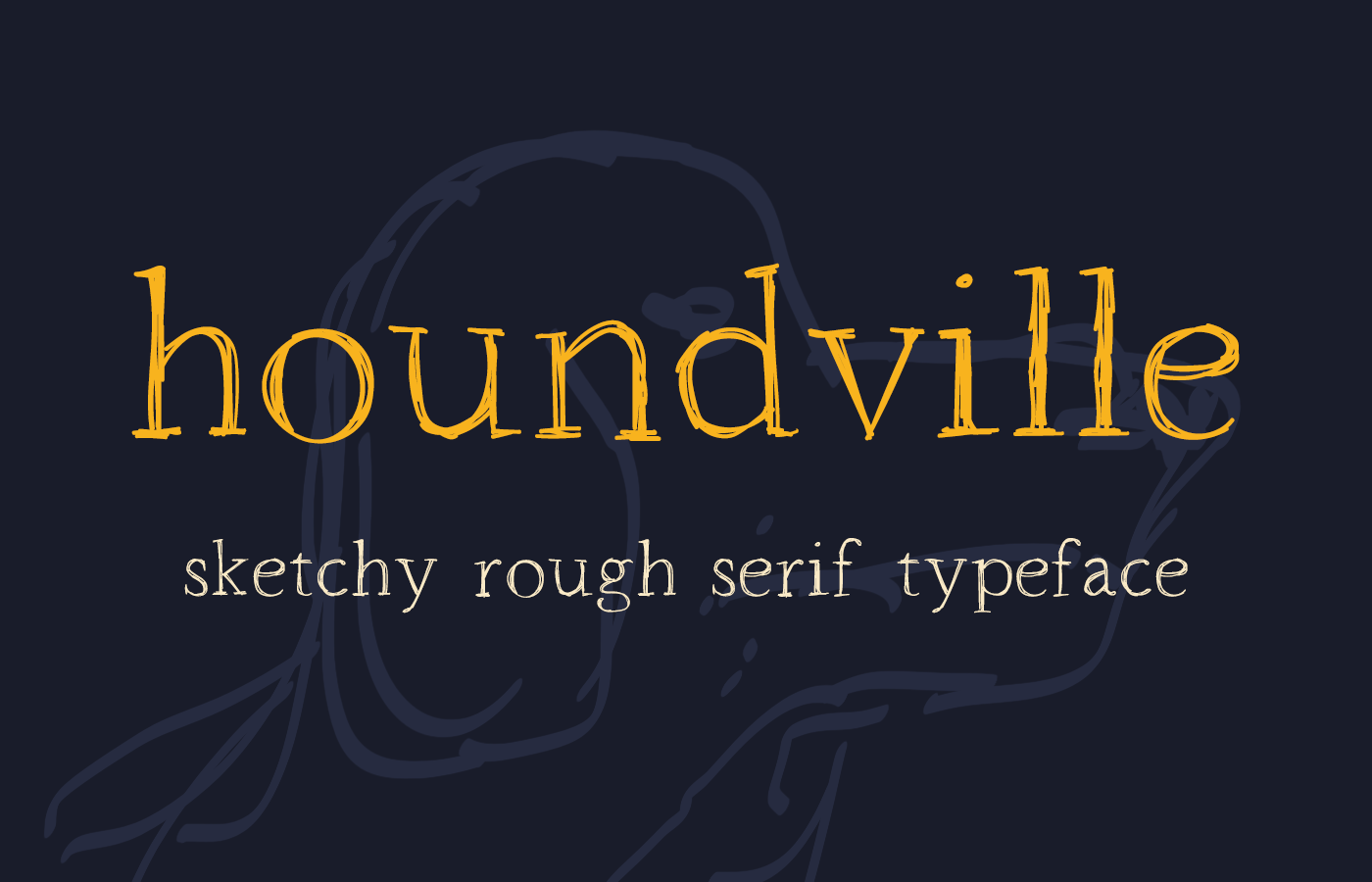
A Houndville é uma fonte serif que surge naturalmente do mundo da escrita a mão. Desenvolvida pelo designer Marco Ballare, esta elegante escolha para seu projeto certamente trará um charme único à sua interface ou qualquer conteúdo editorial. Embora não tenhamos as impressões digitais reais da Houndville, o design em forma de letra a mão sugere uma personalidade cuidadosa e envolvente que se adaptaria perfeitamente a aplicações do dia a dia como textos legíveis para crianças ou qualquer projeto gráfico que valoriza um toque delicado. Através de sua simplicidade, Houndville promete trazer uma atmosfera confortável aos projetos de design, enquanto mantém uma presença elegante e sofisticada.